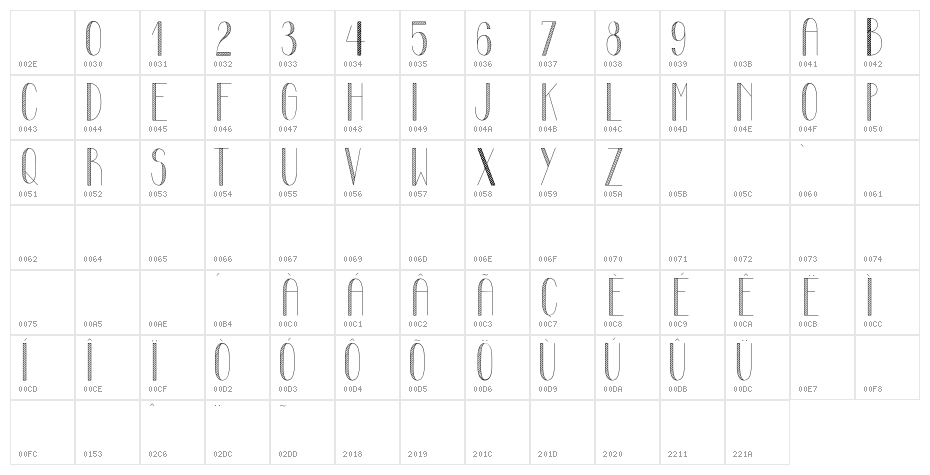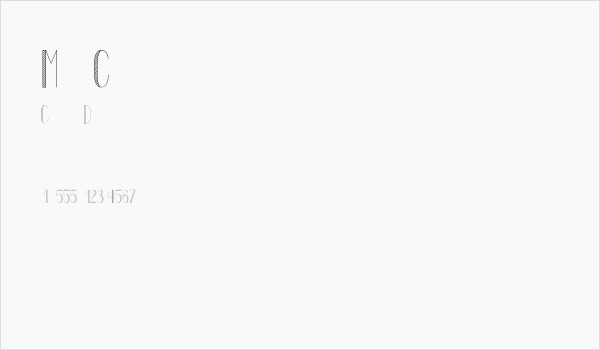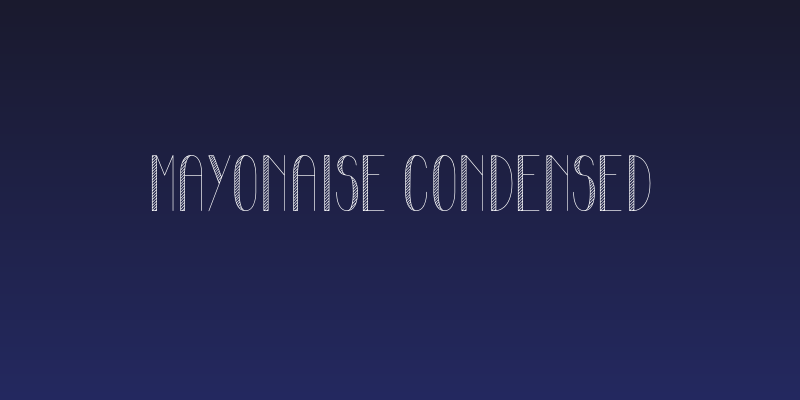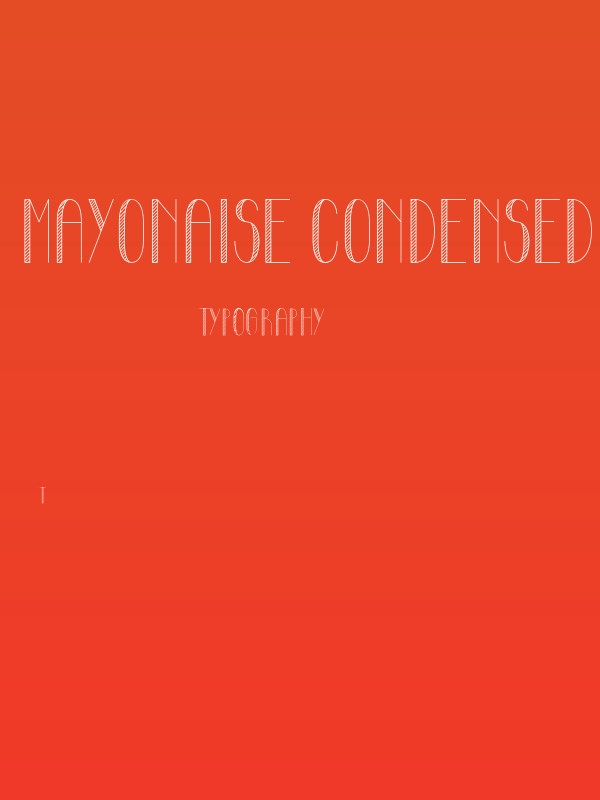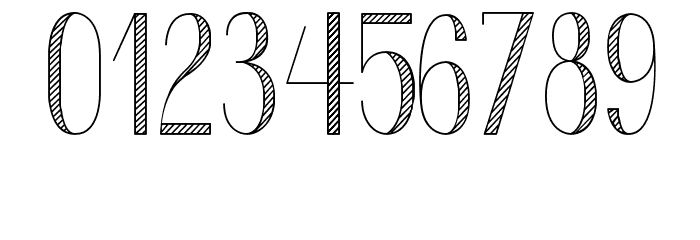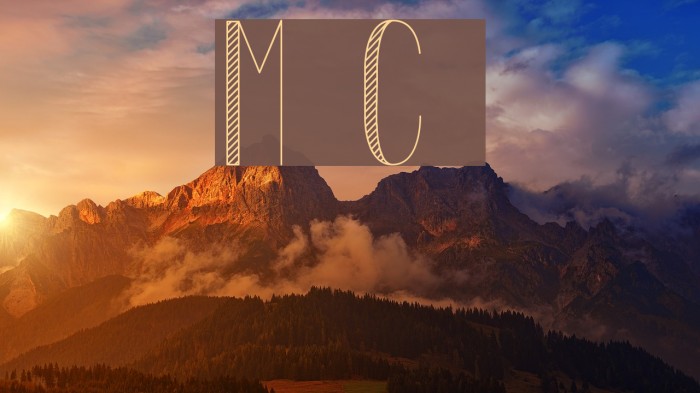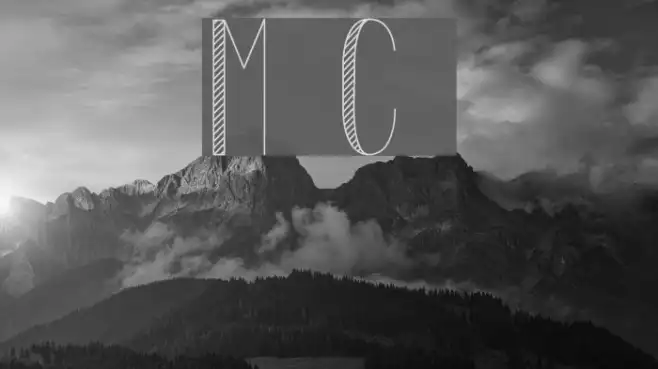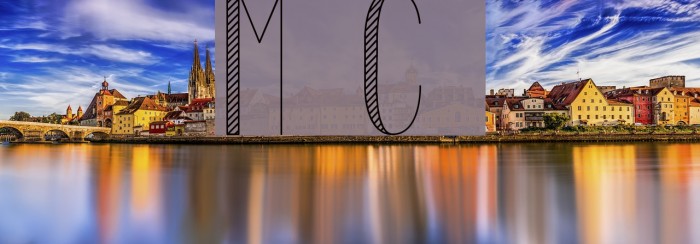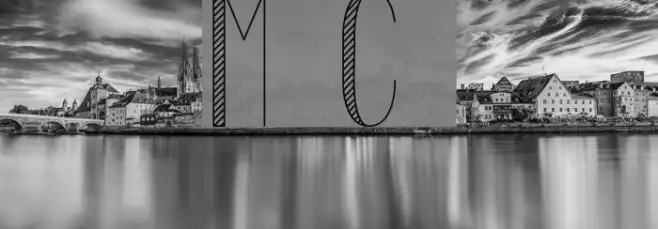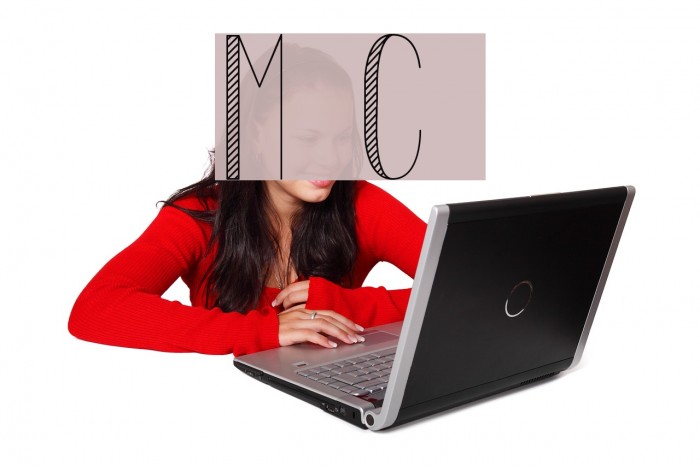
Mayonaise-Condensed Font
| Vorgeschlagene Projekte | Ideal for posters, branding, and packaging design where a modern and artistic touch is desired. |